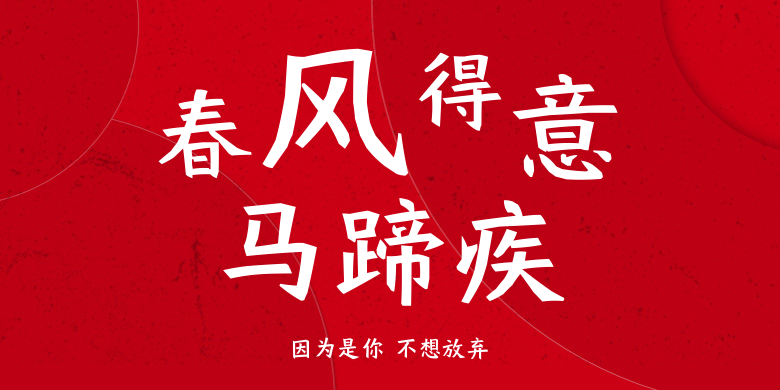
因为是你 不想放弃
因为是你 不想放弃,这款字体结构工整、笔画清晰,兼顾美观与易读性,适用于标题、正文、海报、包装、LOGO 等多种场景。字形优雅稳定,风格百搭耐看,适配日常排版与创意设计,让文字呈现更舒适、更具质感。因为是你 不想放弃一笔一画,皆是细节,以均衡的比例、流畅的线条打造舒适视觉体验,字形端正大气,风格简约现代。无论是商业设计、品牌宣传还是日常排版,都能轻松驾驭,让文字更有格调与力量。因为是你 不想放弃字体下载。